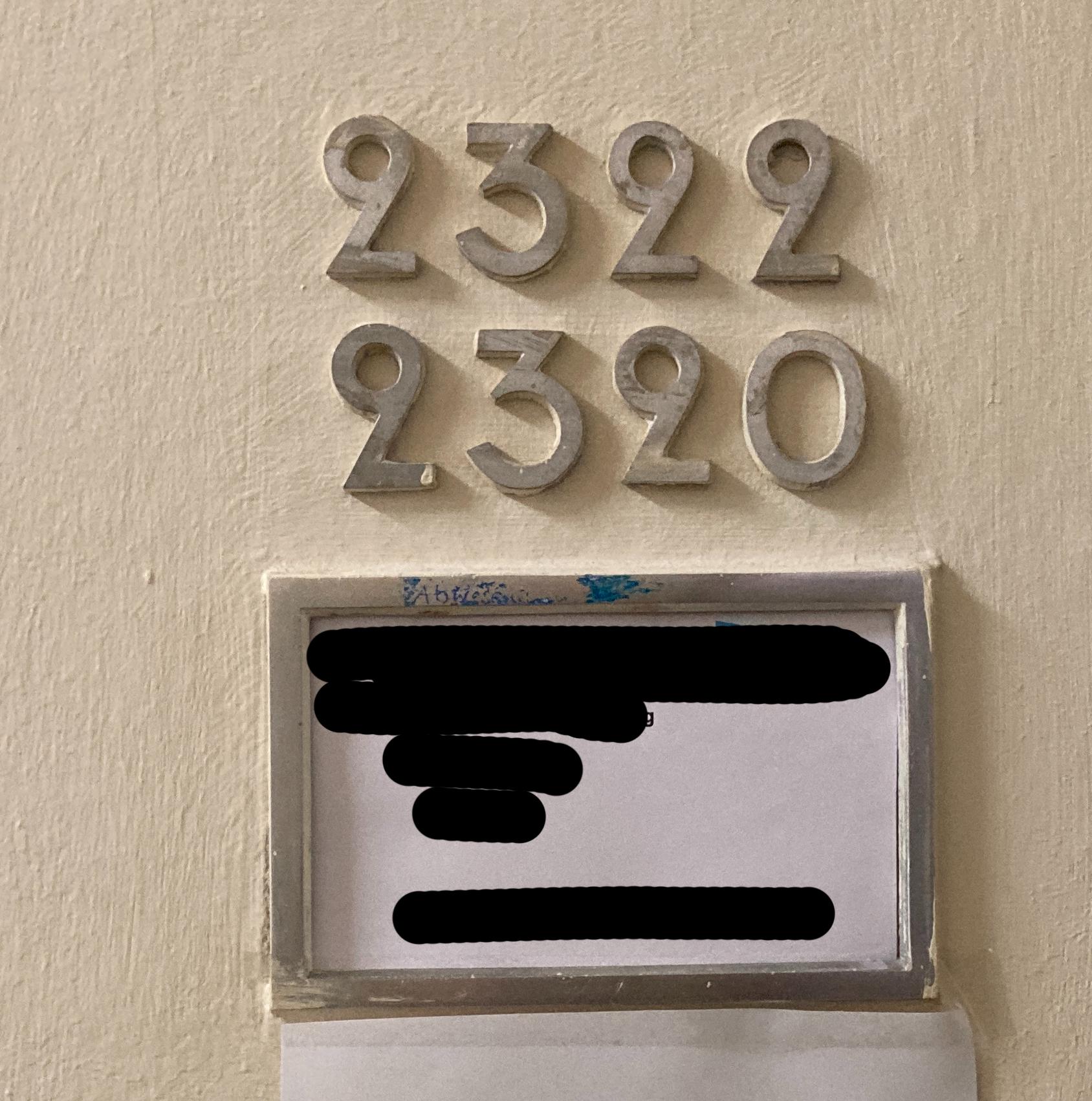
Zu welcher Schrift gehören diese Zahlen? Sie wurde vor 1940 in einem großen Verwaltungsbau verwendet.
Ist die erste eine 2 oder eine 9? :shock:
Im ersten Bild scheint ja die 9 ergänzt worden zu sein, aus – wie mir scheint – einer anderen Schriftart.
Wahrscheinlich gar keiner.
Aber ließe sich mit wenig Aufwand digitalisieren und als Font umsetzen.
Die Zahlen werden als Raumnummern in einem großen Verwaltungsbau aus den 30ern in Berlin-Tempelhof verwendet. Wir würden sie für die denkmalschutzgerechte Restaurierung gerne reproduzieren lassen. Da sie ausschließlich in dieser Form eingesetzt werden, müssten doch simple Vektorgrafiken reichen!? Oder wie würden Sie das machen?
Da ja nur die Ziffern benötigt werden: Ich würde es abreiben (»brass rubbing«), einscannen, eventuell mehrere Varianten einer Ziffer im Photoshop o.ä. übereinander legen, um eine allgemeinere Linie zu finden, und in einem Vektorzeichenprogramm nachbauen.
Das wirkt m. E. nur so, da sie mehr glänzt. Aber sie passt dann doch zur 3 und 6. Sie ist auch nicht richtig ausgerichtet (leicht nach links gekippt)